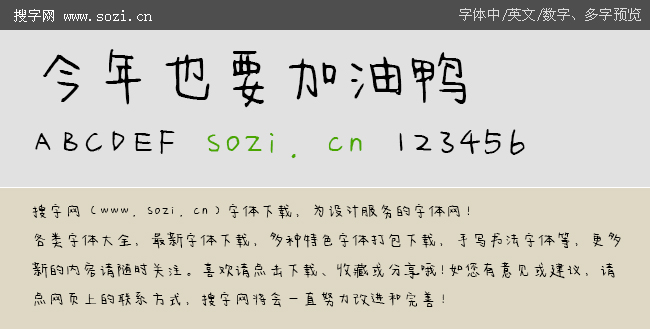
今年也要加油鴨字體
搜字網(wǎng)給大家提供一款今年也要加油鴨字體中文字體下載,今年也要加油鴨字體是由三極字庫(kù)的羅碧霞創(chuàng)作的一款手寫(xiě)風(fēng)格字體。今年也要加油鴨是一款可商用的硬筆手寫(xiě)字體,具有溫柔、婉約、手寫(xiě)風(fēng)、簡(jiǎn)約 的風(fēng)格,包含GB2312規(guī)范的6763字,可以免費(fèi)用于個(gè)人及商業(yè)用途,適用于海報(bào)企宣、書(shū)籍、店鋪、活動(dòng)等場(chǎng)景。